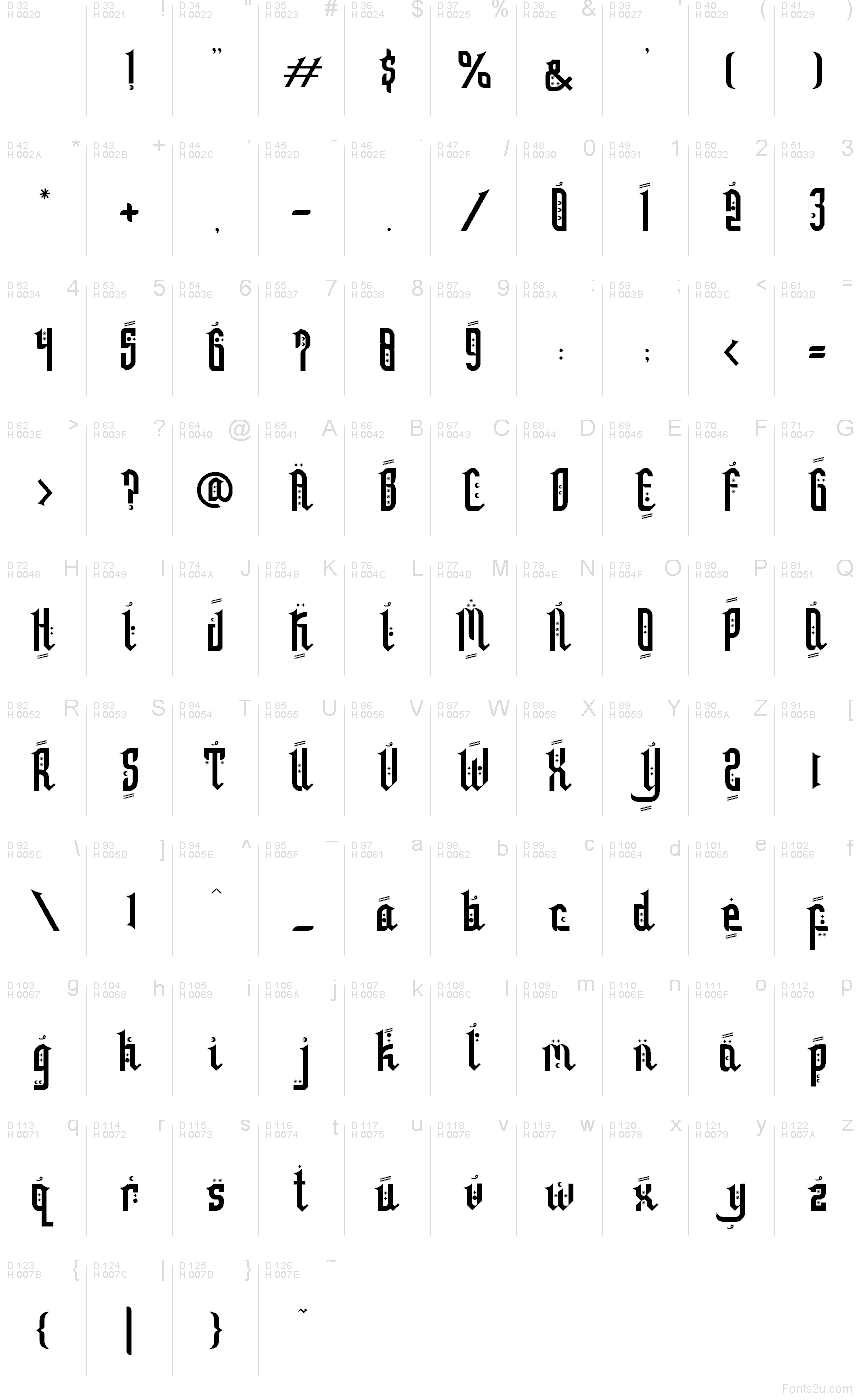
Hikaya Mirage Deco von Putracetol Studio ist eine kostenlose, von arabischer Kalligrafie inspirierte Display-Schrift, die lateinische Buchstaben in eine hohe, kalligrafische Silhouette verwandelt. Geprägt durch spitze Verbindungen, übereinander angeordnete Punkte und kurze Akzentstriche, verleihen diese Anleihen aus der arabischen Schrift dem Design einen feierlichen, dekorativen Rhythmus. Die dichten schwarzen Formen sorgen dabei für Bodenhaftung und machen die Schrift zu einer eigenständigen Display-Typografie statt einer bloßen Imitation.
Dieser Charakter kommt besonders auf Ramadan-Postern, in der Café-Brandidentität, bei Veranstaltungstiteln, Verpackungsdesigns und Social-Media-Headern zur Geltung, wo der Bezug zur arabischen Schrift als Teil des Konzepts wirken soll. Auch Buchcover oder Grafiken für Kulturfestivals erhalten durch sie eine besondere Note, vor allem wenn die Punktcluster und markanten vertikalen Formen genutzt werden, um kurze Wörter und Namen wirkungsvoll einzurahmen.